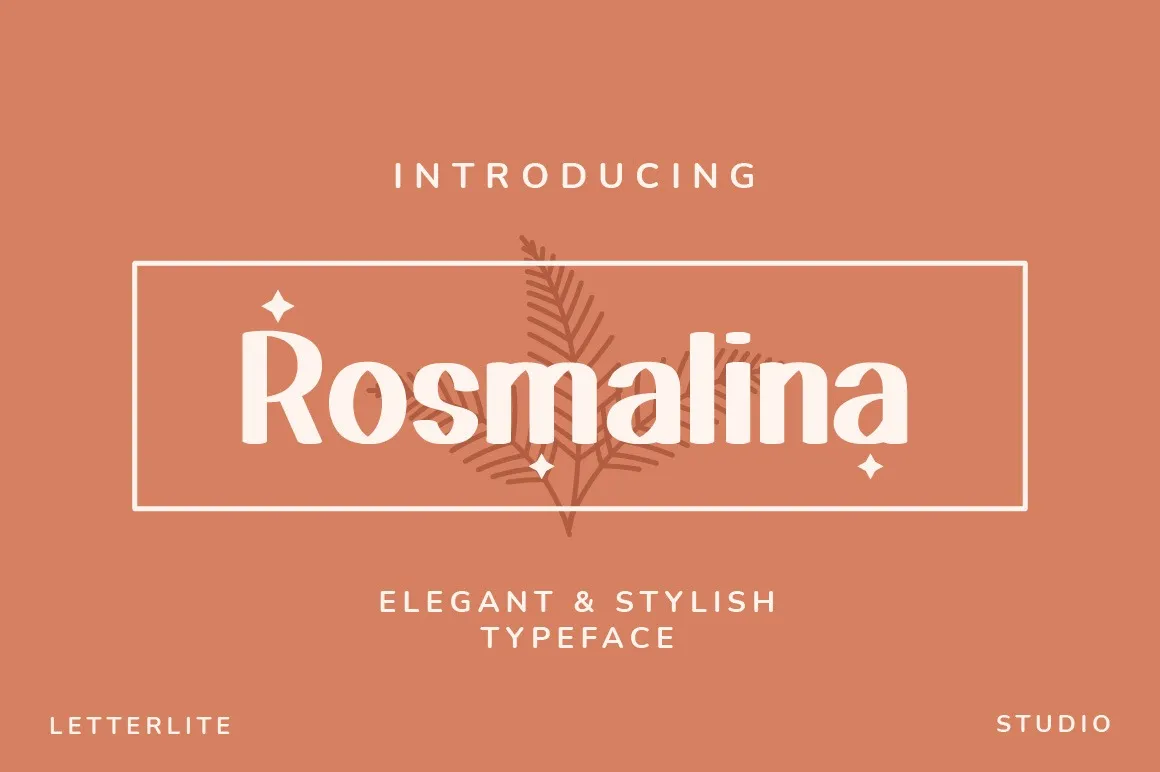
A Rosmalina Font é uma tipografia sans-serif que surgiu do toque suave e espontâneo de uma mão humana. Inspirada no movimento tranquilo e agradável, essa letra se destaca por seu aspecto natural e harmonioso, proporcionando um contraste elegante para qualquer projeto gráfico. O design é tão versátil quanto pode ser, permitindo que seja usada tanto em grandes tamanhos quanto em pequenos detalhes, tornando-a uma escolha ideal para diversos ambientes de aplicação, desde materiais de marketing a elementos de design web. Seu design parece desenhar-se naturalmente na paisagem da sua obra, refletindo tranquilidade e beleza que se integra perfeitamente ao universo digital moderno.